Лучшие типографские шрифты для создания логотипов: шрифты для логотипов
С ростом онлайн-бизнеса креативным дизайнерам необходимо раскрыть суть бизнеса в логотипе. Теперь, когда к Интернету приходят многие компании, не только электронная коммерция, но и другие типы веб-страниц, у всех них одна и та же потребность: создать логотип. А как дизайнеру нужно хорошо шрифты для логотипов, которые удовлетворят всех ваших клиентов.
По этой причине сегодня мы сосредоточимся на том, чтобы дать вам различные шрифты для логотипов, не только лучшие, но и пользующиеся большим спросом, бесплатные, те, которые придадут особый оттенок вашему проекту… Вы хотите знать, какие из них мы выбрали?
Характеристики шрифтов для логотипов
Выбор шрифта для логотипов звучит легко, но на самом деле это не так. Эти типы шрифтов для логотипов должны иметь ряд характеристик, чтобы они идеально выполняли свою миссию. А это что? Хорошо:
- Его должно быть легко узнать и запомнить. Другими словами, когда вы его видите, вы отождествляете его с компанией, в честь которой он назван. Если вы разместите слишком замысловатый логотип с непонятным шрифтом, он вряд ли сможет проникнуть в широкую публику.
- Меньше — больше. Также в типографских шрифтах. Вы должны иметь в виду, что одного или максимум двух источников более чем достаточно. Если вы будете использовать больше, у клиентов возникнет чувство недоверия. Если ваш клиент — крупная компания, сделайте ставку на использование только одного шрифта.
С другой стороны, если это небольшие компании, вы можете центрировать шрифт для названия компании, а другой — для слогана (если он есть). - Классика. Возможно, ваш клиент захочет использовать модный шрифт, потому что он его видел, читал и т. Д. Попробуйте выбросить это из головы. Мода мимолетна, и в конце концов у вашего логотипа будет срок годности, поэтому через короткое время вам придется его сменить, потому что он устареет.
Типы типографских шрифтов для логотипов
Еще один аспект, который следует учитывать, заключается в том, что внутри шрифтов существует несколько типов шрифтов, которые сгруппированы в 5 больших групп:
- Шрифты с засечками. Они самые классические и самые старые, поскольку речь идет о XNUMX веке (с этой даты их начали использовать). Используя его в логотипе, вы придадите ему консервативный вид, хотя он не значит старомодный, а элегантный и утонченный.
- Шрифты без засечек.
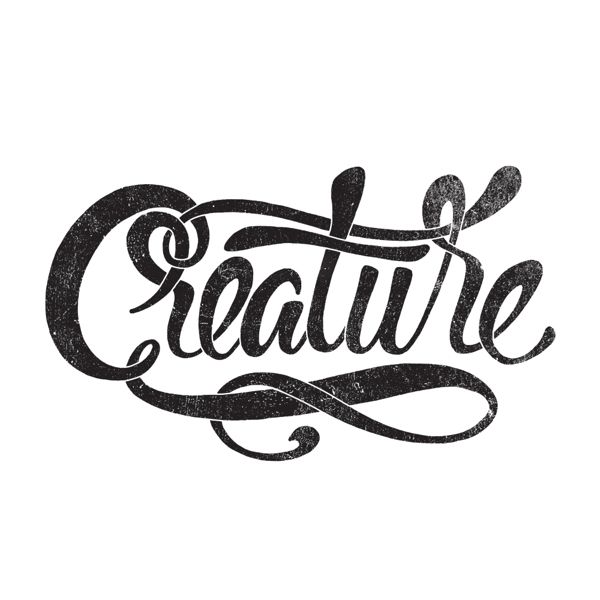
Они идут больше к основам, удаляя орнаменты предыдущего и стремясь получить прямые и чистые линии. Его цель состоит в том, чтобы дать ясность и быть очень легкими для понимания и понимания того, что относится к логотипу. - Шрифт Slab Serif. Этот фонтан, вариант предыдущего, возник в XNUMX веке и характеризуется сочетанием двух вышеперечисленных. Он стремится создать солидный визуальный эффект, но в то же время модернизировать для своего времени. Они более округлые или угловатые, а не такие прямые, как другие. В свою очередь, они передают уверенность в бренде и креативность.
- Скриптовые шрифты. Estas empezaron a surgir en el siglo XX y llamaban mucho la atención por un aspecto más de “escritura a mano”. Lo que buscaban es que fueran letras que, en sí mismas, ya tuvieran florituras, diseños diferentes, etc. El objetivo, con esas formas curvas y llenas de diseños, es crear una sensación de ingenio y creatividad.
- Источники отображения.
Также известные как декоративные шрифты, они ищут, чтобы буквы сами по себе были дизайном, таким образом, чтобы он воспроизводился с полностью разработанным логотипом (буквы не обязательно должны быть шрифтами, а скорее проектом). Что касается того, что они выражают, они стремятся дать ощущение веселья, развлечения и чего-то неформального.
Шрифты для логотипов: самые лучшие
А теперь посмотрим, какие типы шрифтов для логотипов мы можем порекомендовать.
Бодони
Источник: Fontgeek
Это шрифт для логотипов, который вы видели в бренде у всех на слуху, особенно если вам нравится мода. Мы говорим о VOGUE. Его логотип имеет этот шрифт, и он является одним из наиболее часто используемых для предприятий, связанных с модой, элегантностью, роскошью, гламуром и т. Д.
Garamond
Гарамонд — это типографика, которая часто используется для книг, потому что он имеет элегантный дизайн, а не такой простой и простой. У этого тоже есть неплохой успех.
Впервые он был представлен в 1900 году, а именно на Всемирной выставке в Париже, и постепенно он внес свой вклад в повседневную жизнь. Он очень выразительный и легко используется в профессиональных логотипах, которые хотят придать своим брендам вневременной характер.
Нунито Санс
Как следует из названия, это шрифт без засечек. это очень простой в том, что он делает ставки на четкие линии, не слишком сильный и очень понятный для чтения. Что для дисплеев идеально.
Это обновление классического шрифта без засечек — одно из самых распространенных в брендинге. Этот шрифт идеально подходит для логотипов из-за его четкого и чистого внешнего вида, а также его удобочитаемости.
Эти факторы также делают его отличным выбором для цифровых приложений, таких как веб-сайты и приложения, для обеспечения простоты использования и положительного впечатления посетителей. Яркими примерами использования Helvetica Now в логотипах являются автомобильная марка Jeep и производитель электроники Panasonic.
4. Avenir